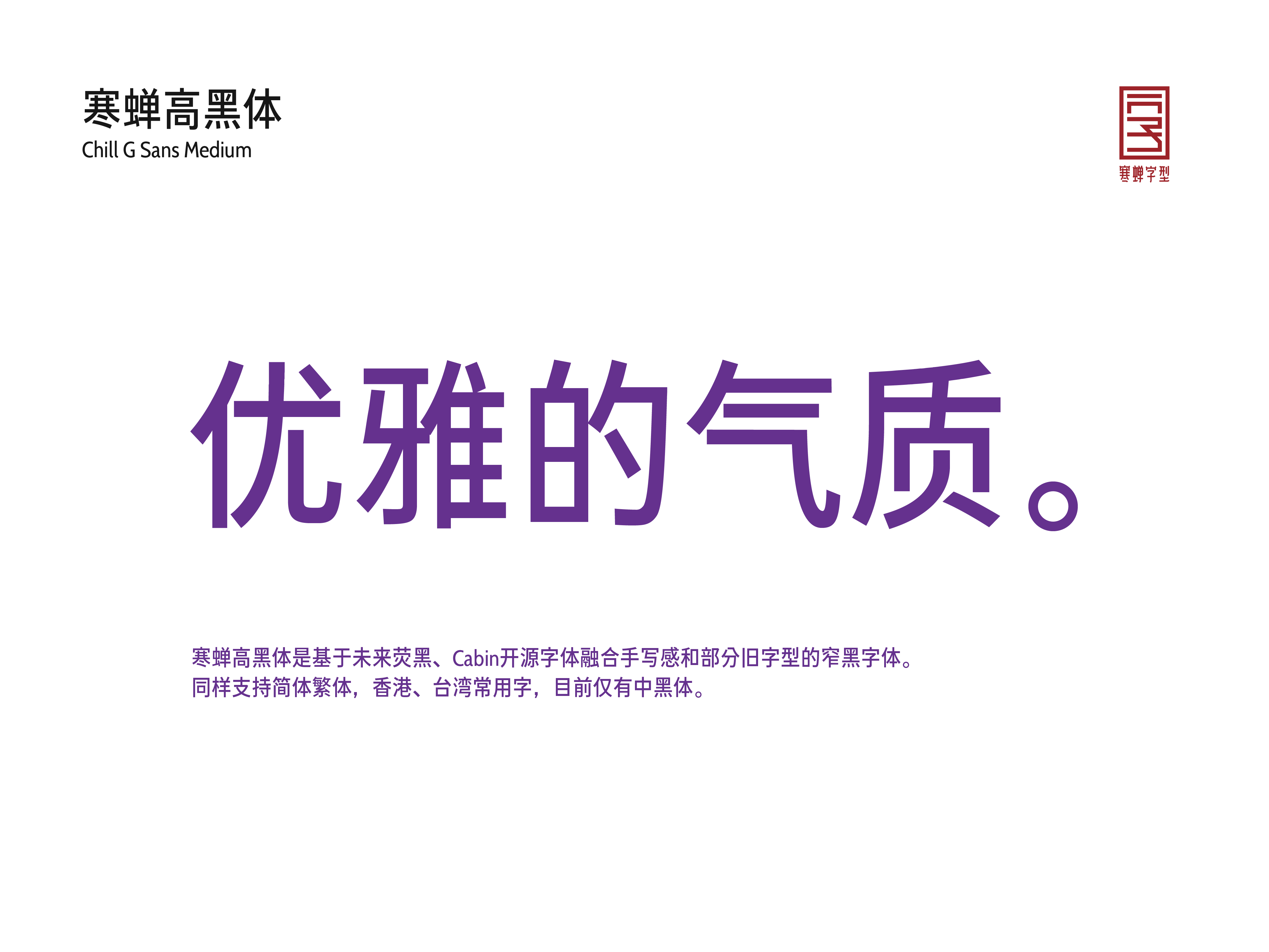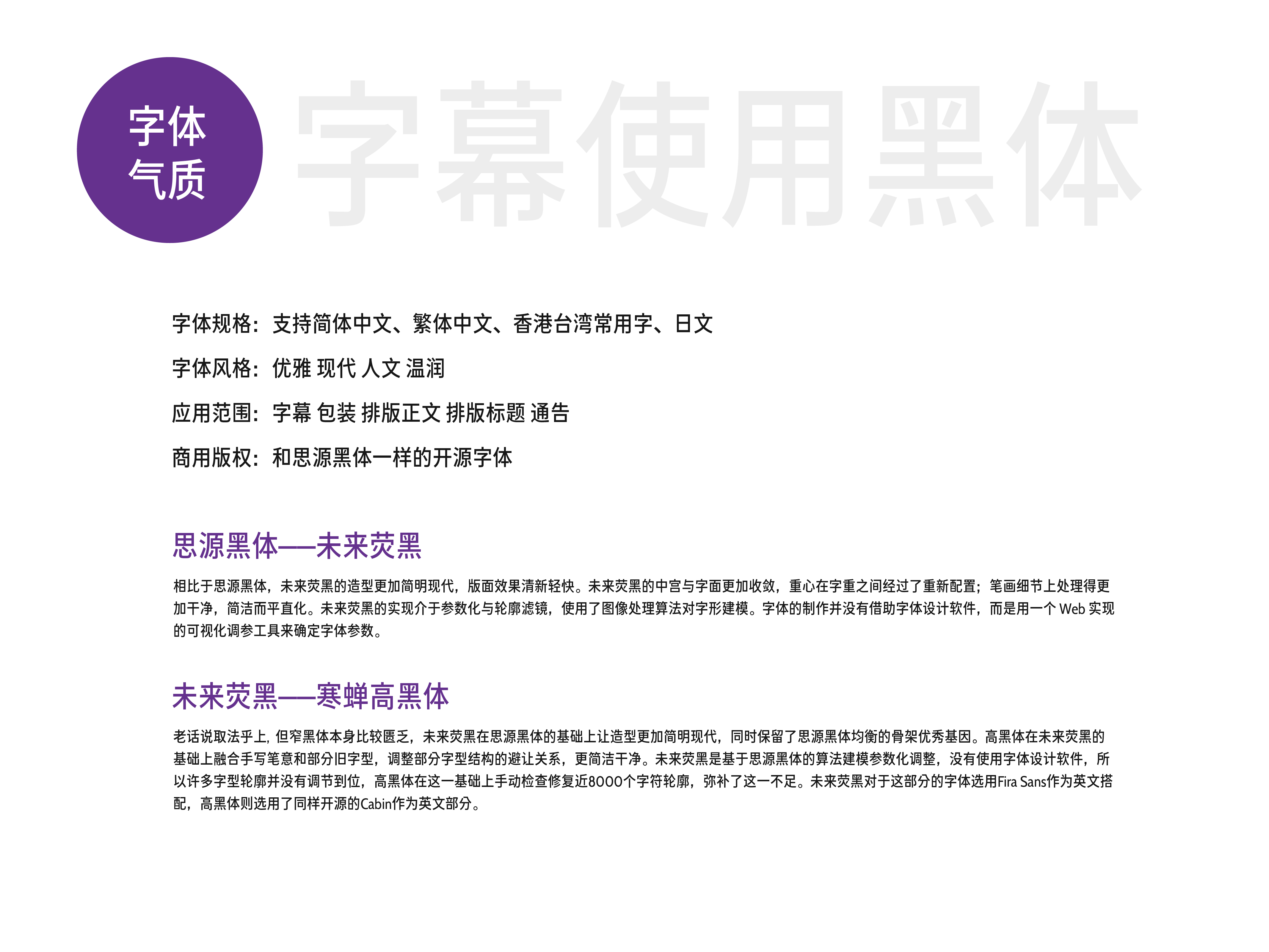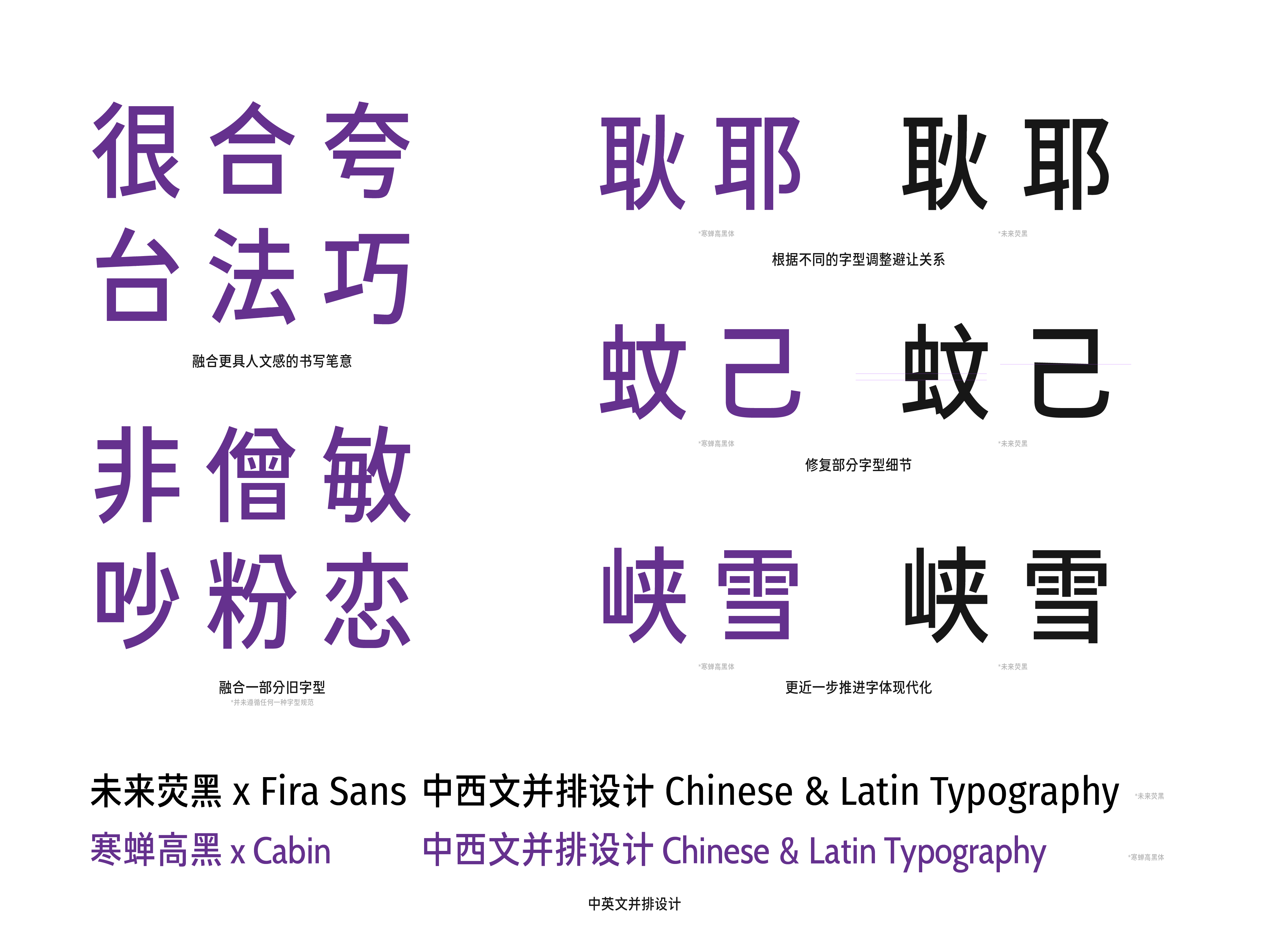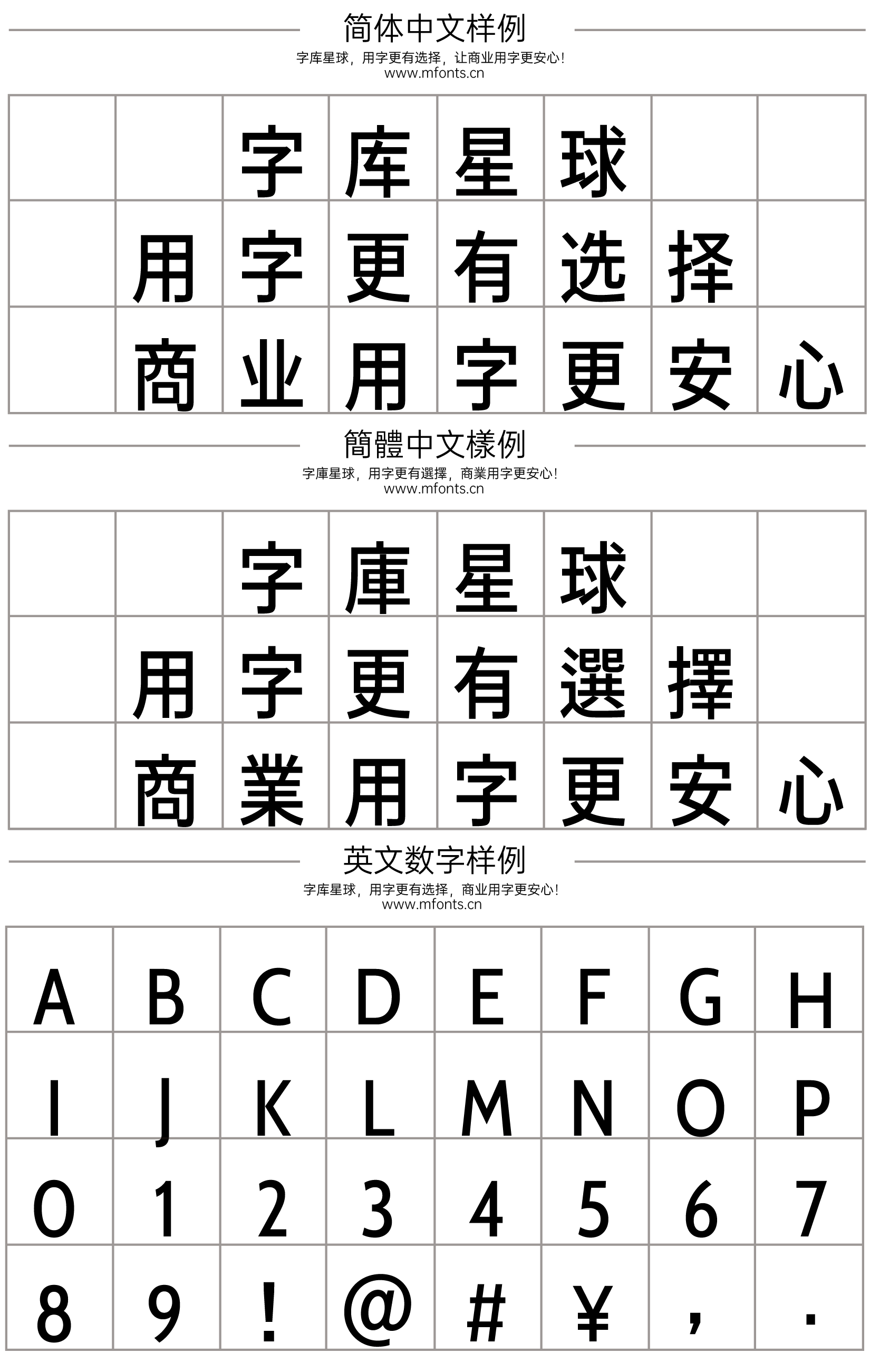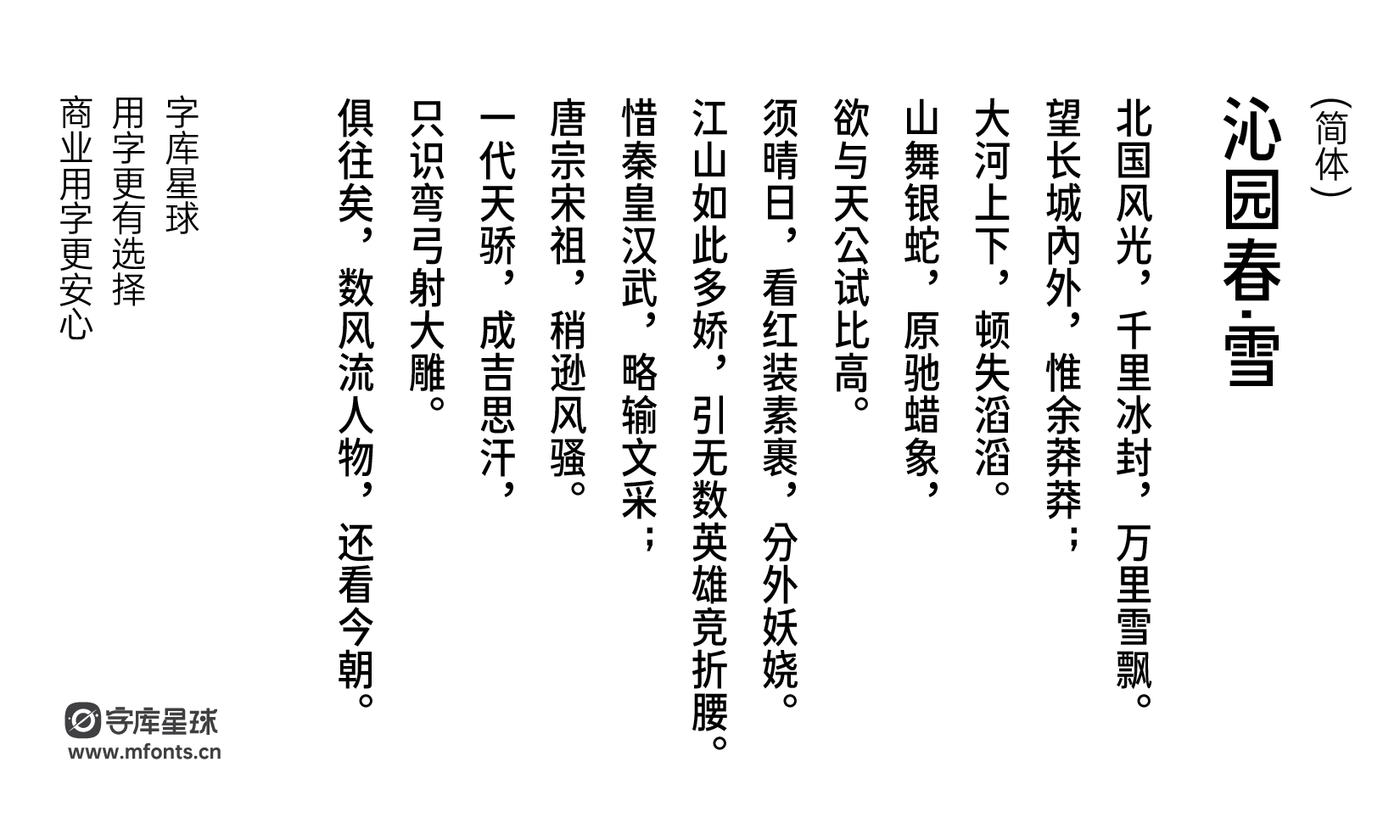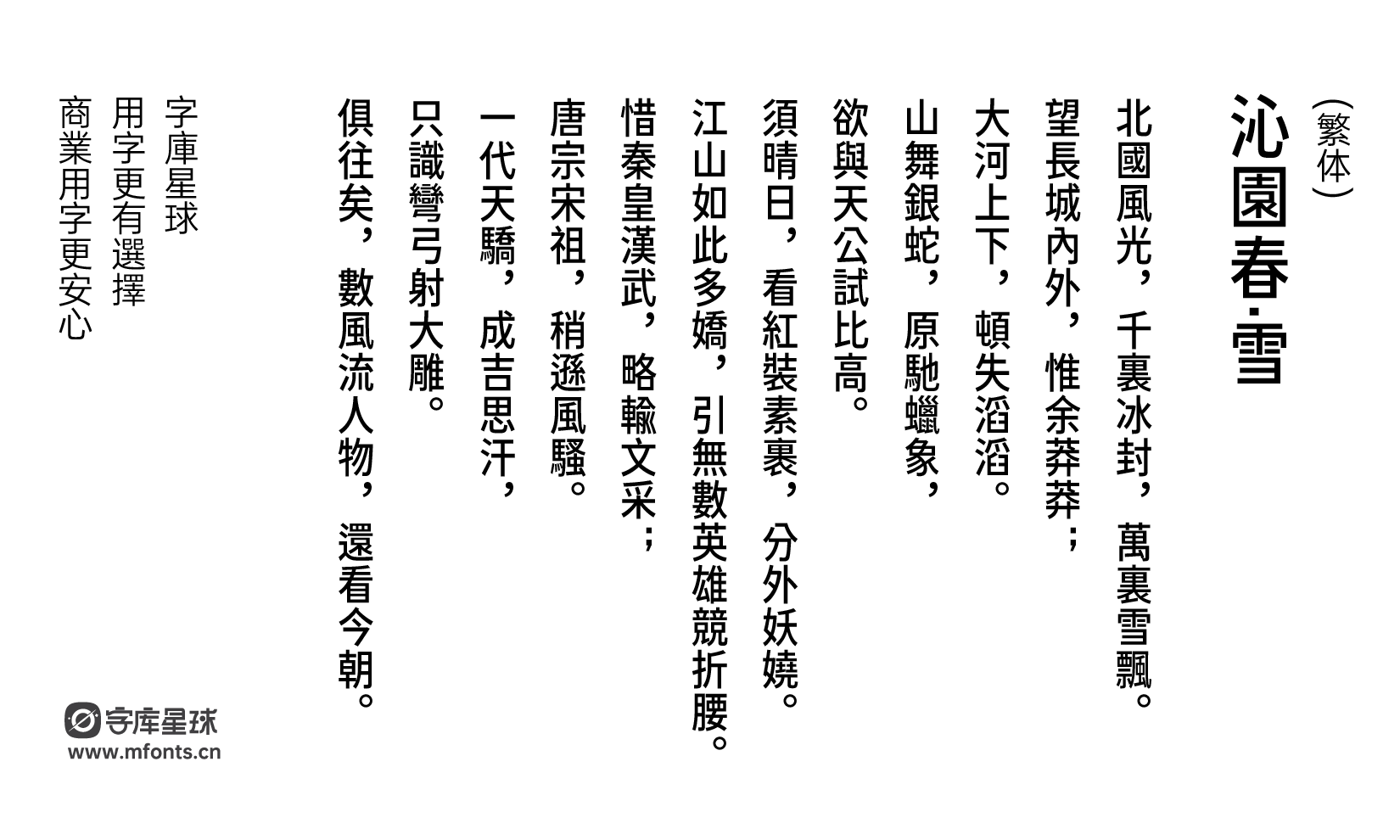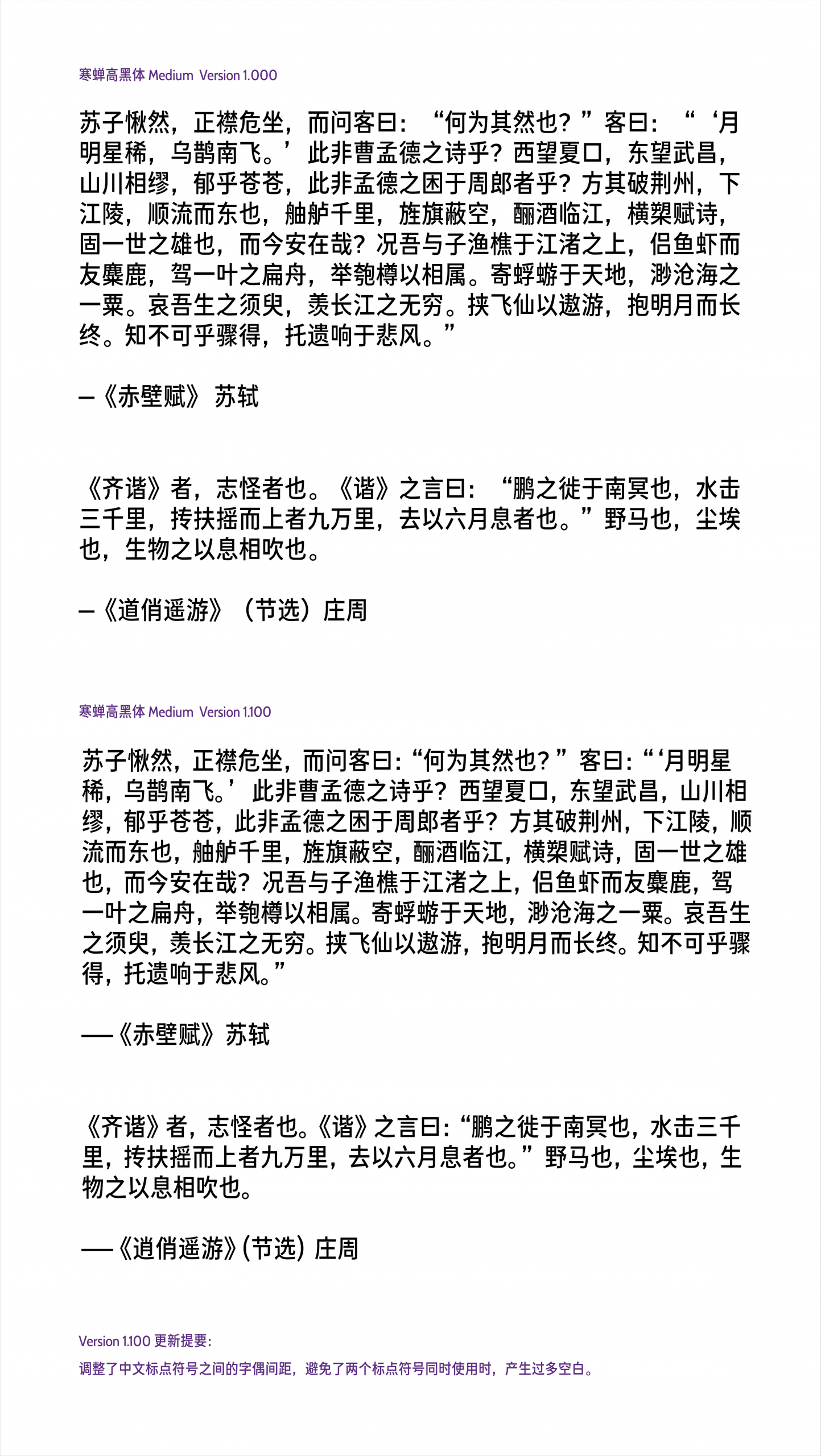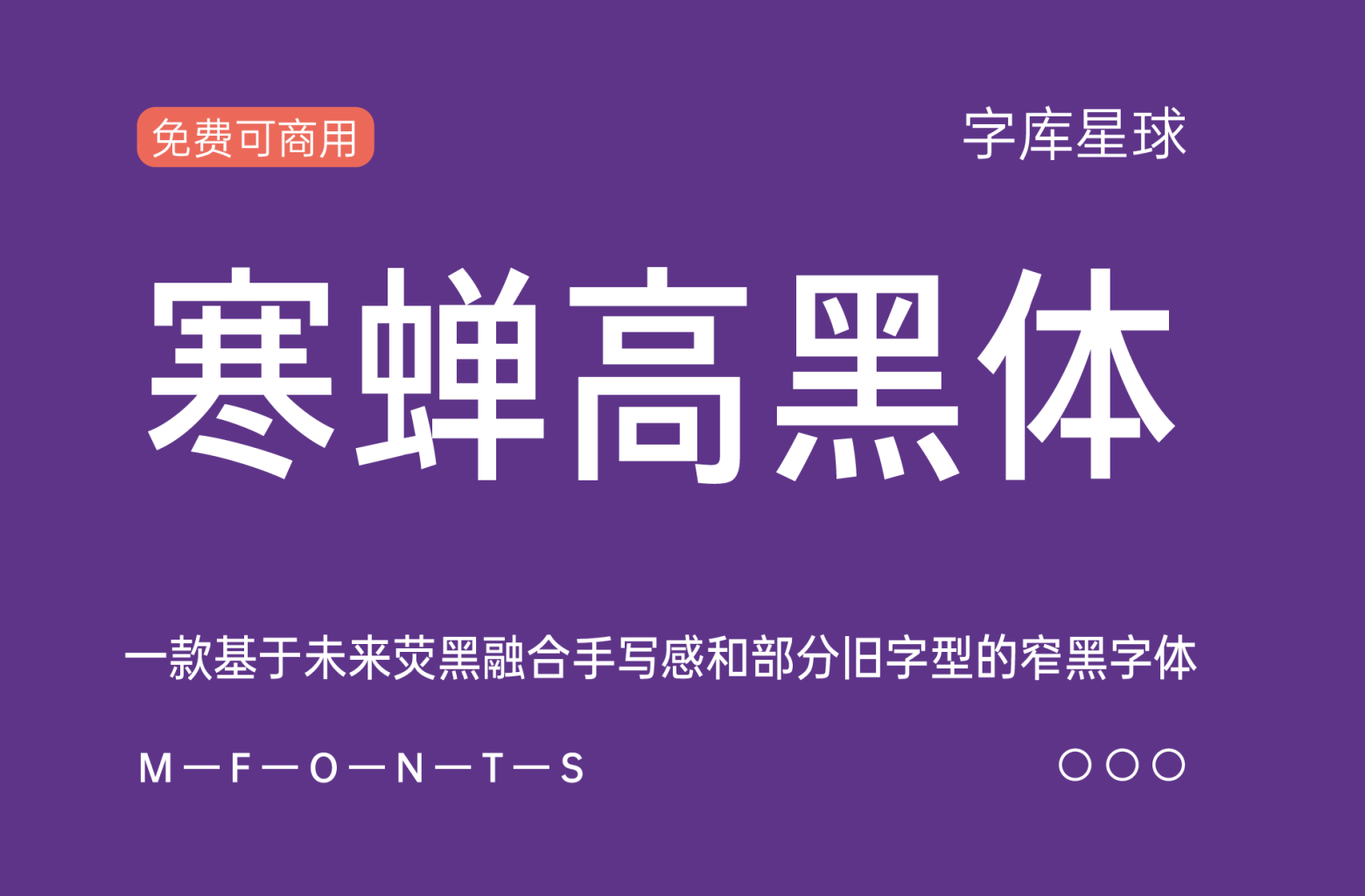
寒蝉高黑体
寒蝉高黑体是基于未来荧黑、Cabin开源字体融合手写感和部分旧字型的窄黑字体。
同样支持简体繁体,香港、台湾常用字,目前仅有中黑体。
字幕使用字体
字体规格:支持简体中文、繁体中文、香港台湾常用字、日文
字体风格:优雅 现代 人文 温润
应用范围:字幕 包装 排版正文 排版标题 通告
思源黑体——未来荧黑
相比于思源黑体,未来荧黑的造型更加简明现代,版面效果清新轻快。未来荧黑的中宫与字面更加收敛,重心在字重之间经过了重新配置;笔画细节上处理得更加干净,简洁而平直化。未来荧黑的实现介于参数化与轮廓滤镜,使用了图像处理算法对字形建模。字体的制作并没有借助字体设计软件,而是用一个 Web 实现的可视化调参工具来确定字体参数。
未来荧黑——寒蝉高黑
老话说取法乎上, 但窄黑体本身比较匮乏,未来荧黑在思源黑体的基础上让造型更加简明现代,同时保留了思源黑体均衡的骨架优秀基因。高黑体在未来荧黑的基础上融合手写笔意和部分旧字型,调整部分字型结构的避让关系,更简洁干净。未来荧黑是基于思源黑体的算法建模参数化调整,没有使用字体设计软件,所以许多字型轮廓并没有调节到位,高黑体在这一基础上手动检查修复近8000个字符轮廓,弥补了这一不足。未来荧黑对于这部分的字体选用Fira Sans作为英文搭配,高黑体则选用了同样开源的Cabin作为英文部分。